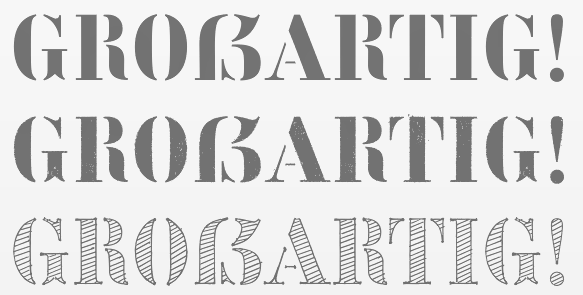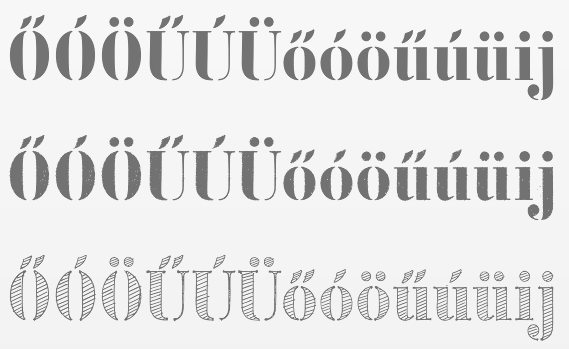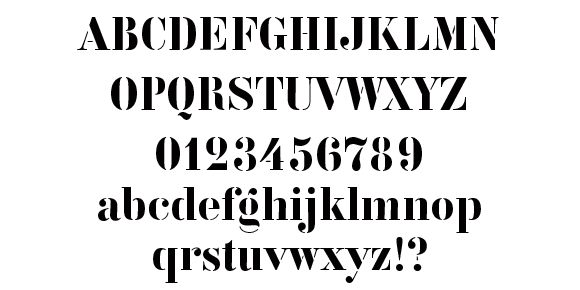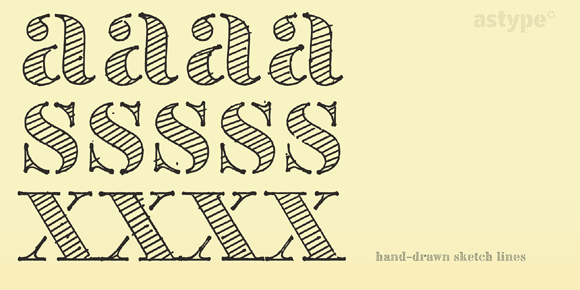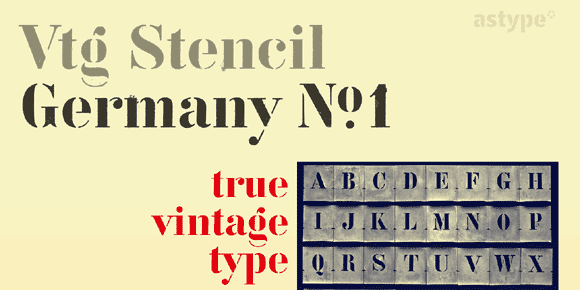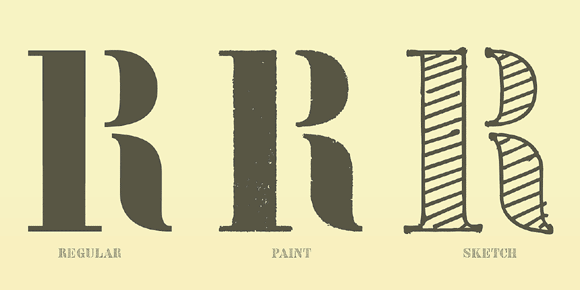
astype: Vtg Stencil Germany No.1
Astype veröffentlicht Schablonenfonts die auf historischen Signierschablonen aus dem Deutschland der Kaiserzeit basieren.
Die Font-Familie besteht aus den drei Stilen Regular (technisch saubere Formen), Paint (schablonierte, raue Formen) und Sketch (Strichzeichnung).
Die Stile Paint und Sketch bieten vier zusätzliche Varianten jedes Grundbuchstaben und der Ziffern an. Dadurch wird eine natürlichere (handgemachtere) Anmutung des Schriftbildes erzeugt.
Über das OpenType-Feature kontextbedingte Varianten ist eine Art Zufallsgenerator eingebunden der die einzelnen Buchstabenvariationen dynamisch bei der Texteingabe rotiert.
Selbst für das Ungarische eignet sie sich ganz hervorragend. Akuts und Doppelakuts ähnlicher Anmutung waren früher gerade in »selbst geschnitzten« Beschilderungen weit verbreitet, finden sich heute aber nur noch selten in Digitalschriften. Bravo!